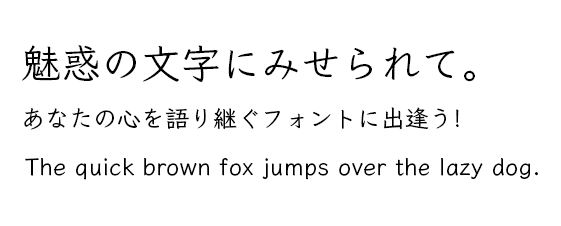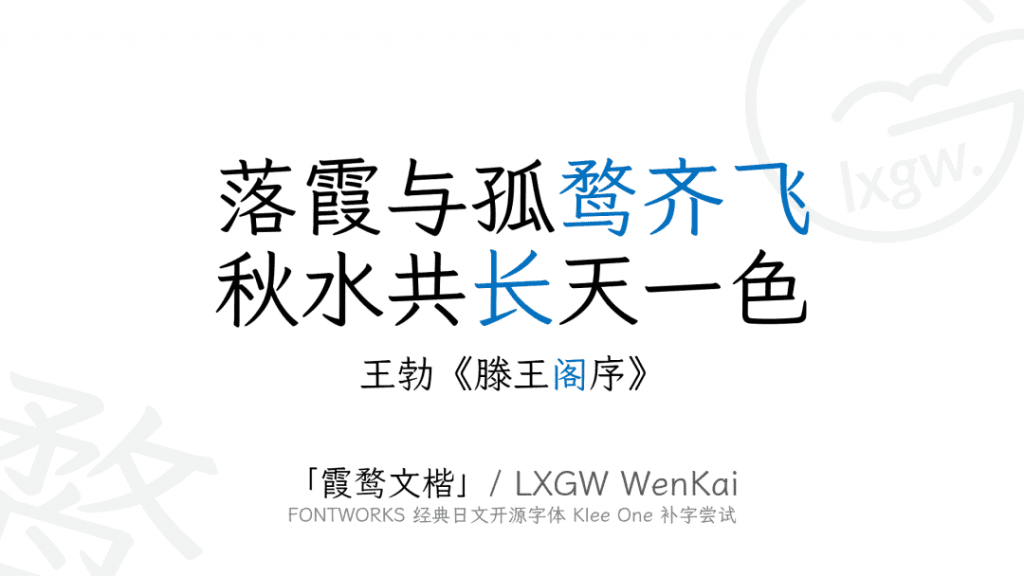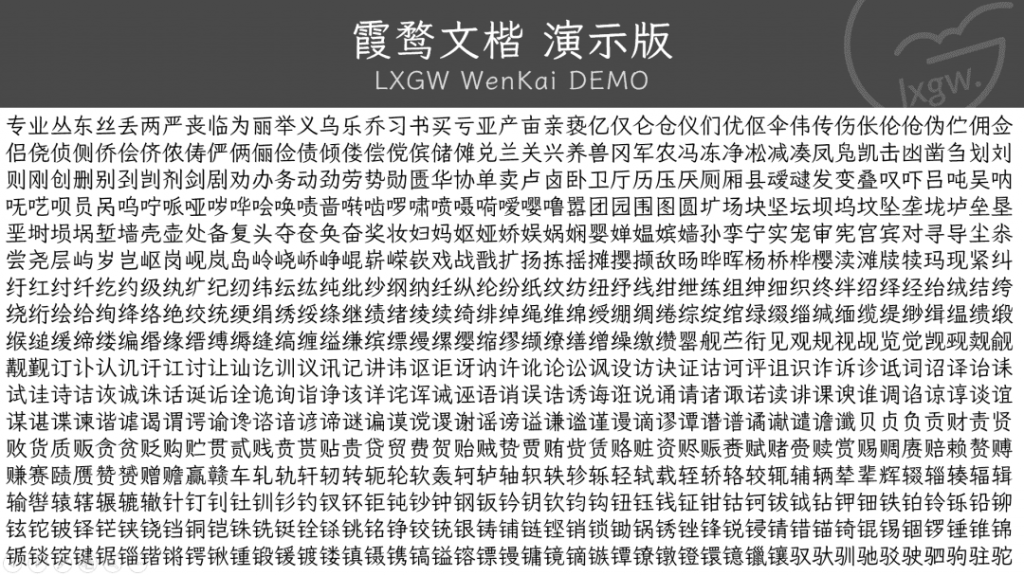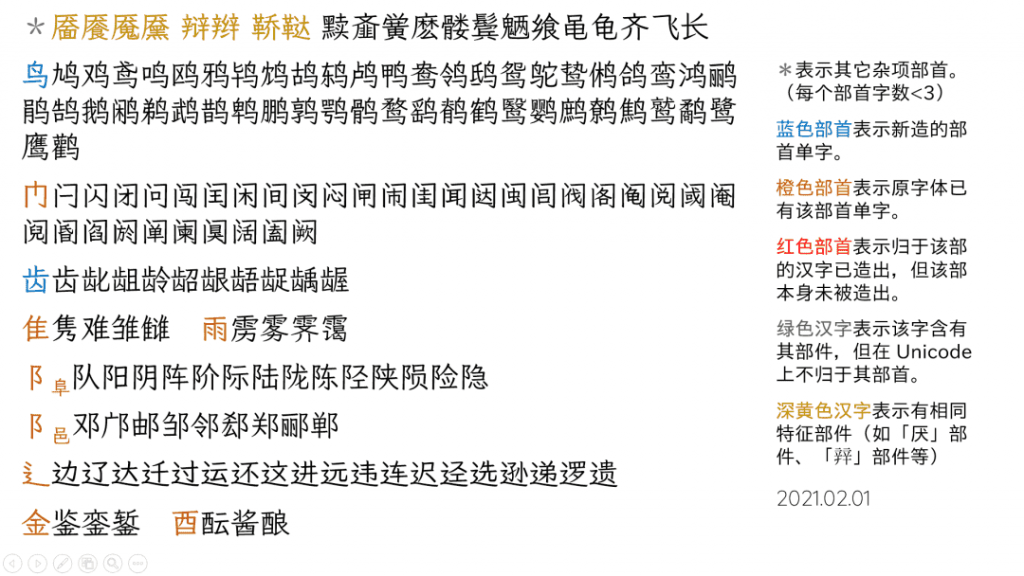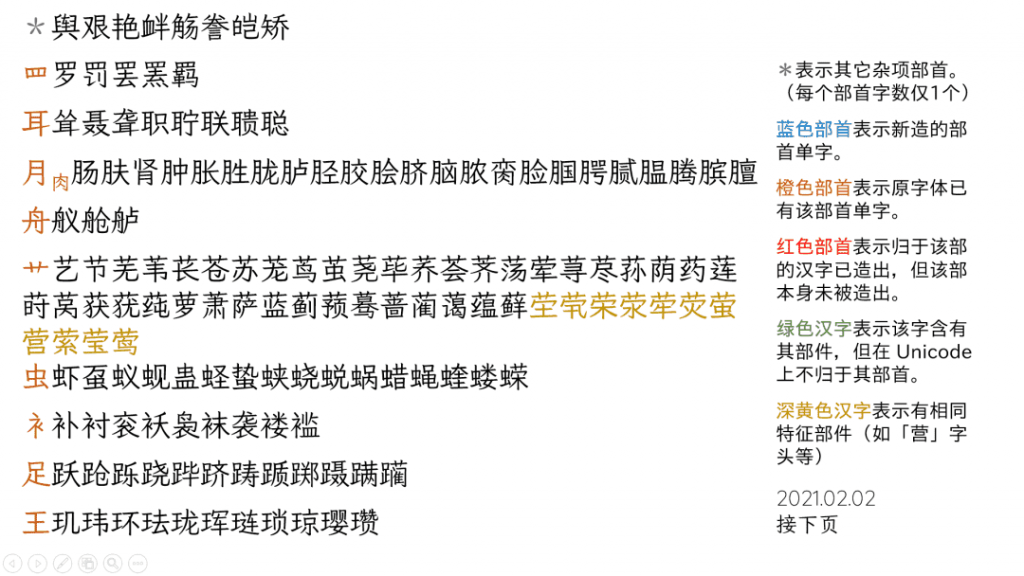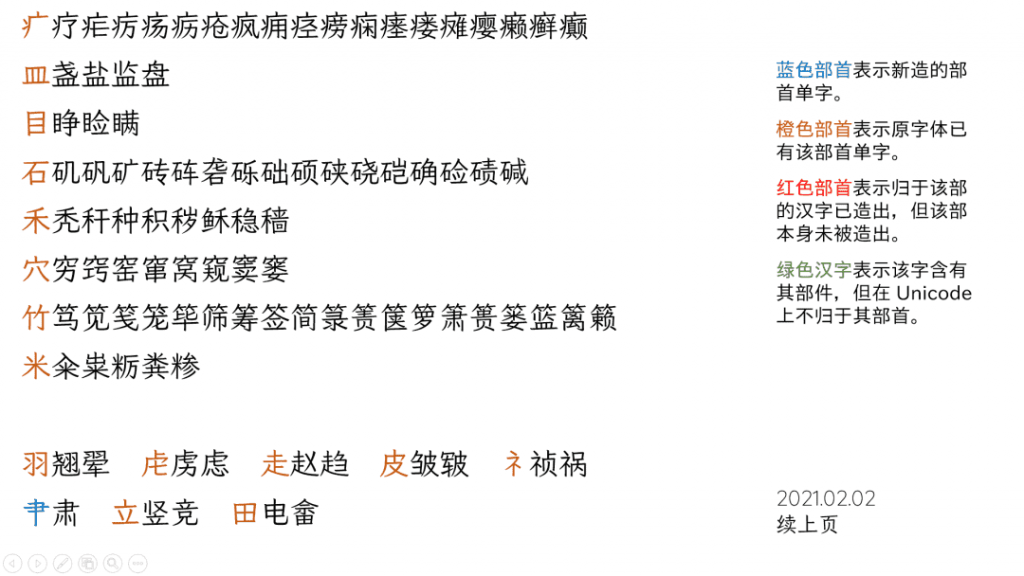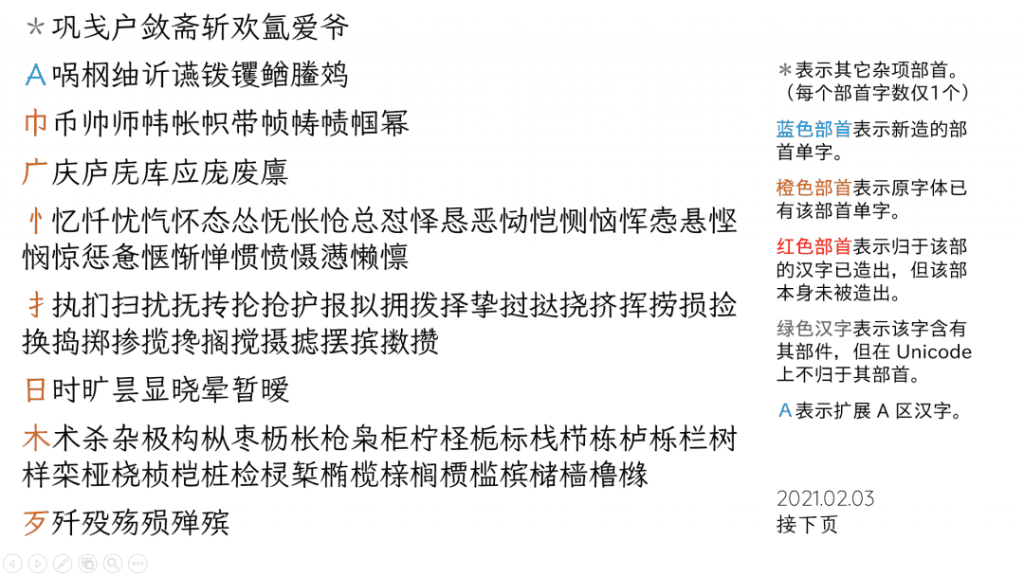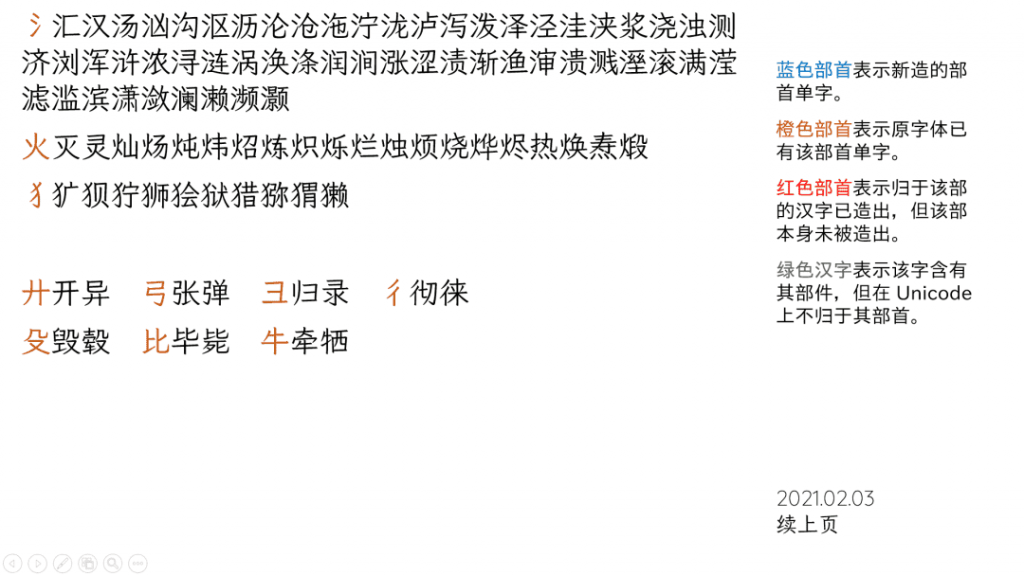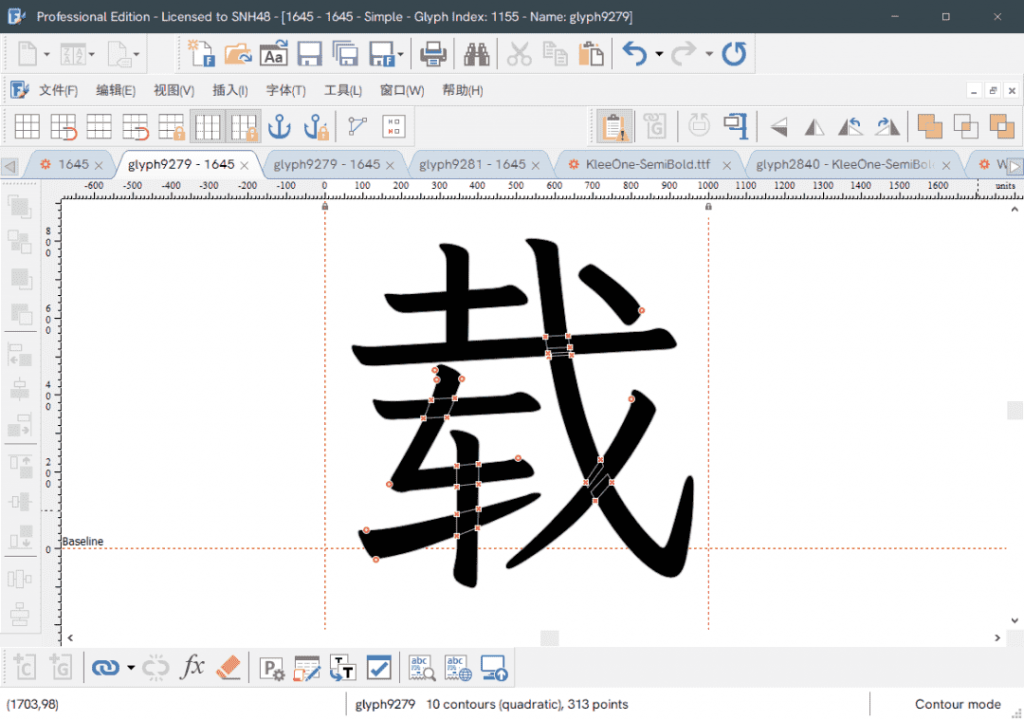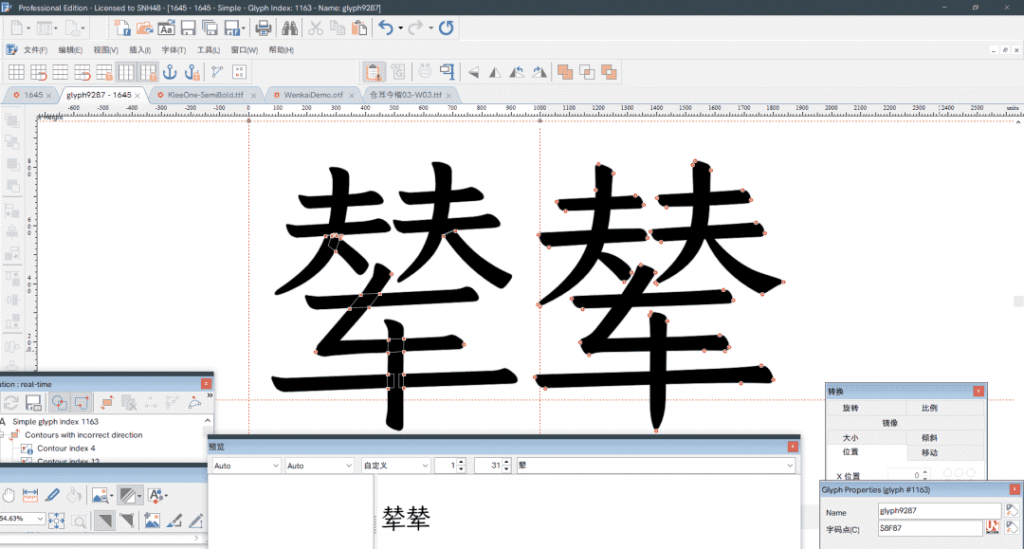
前言
前段时间,日本著名字体厂商 FONTWORKS 在 GitHub 上释出了 7 款开源日文字体,分别为 Train、Klee、Stick、Rock-n-Roll、Reggae、Rampart 和 DotGothic16。7 款开源日文字体各有各的特点,其中我最感兴趣的,当属 Klee。
FONTWORKS 公司出品过很多以西方艺术家名字为代号的字体,比如之前分享过的 Seurat、Rodin、Cezzane 等。这款字体的名字叫 Klee,是以德裔瑞士籍画家保罗•克利(Paul Klee,1879-1940)命名的。这款字体是一款日式的教科书字体(日本小学教科书的标准书写字体,相当于我们的规范楷书)。原版只有 Medium 和 Semibold 两个字重,为 Pro 字集,含有近 8000 个汉字。
初衷
这是一款本人非常喜欢的字体,有着日本教科书体的写法,兼有仿宋和楷体的特点,可读性高。一些 DIY 字体爱好者曾先后用仿宋、刻本仿宋、仓耳今楷补全这款字体,做为手机系统的美化字体移稙在 iOS、Android 等手机系统中,受到很多机友的欢迎。
不过这样补全的字体有一些不足之处。 第一,原有字体和后补字体之间有着一定的差异,致使一些不同的文字(如 Klee 原有汉字与后补简体字)混排之后会有违和感。 第二,由于补字所用的字体(如刻本仿宋、仓耳今楷等)为商业版权字体,补全之后不可用于商业用途,还会有侵权的风险。
鉴于此,本人开始了为 Klee 这一高质量的日文字体补全简体字的尝试。选取较粗的 SemiBold 字重,截至 2021.02.03,已造了1650 个字,已基本补完原字体(Klee One)所含繁体字对应的简体字。部分字稿如下图所示,持续更新。补全后的字体拟命名「霞鹜文楷」。
字稿
截至 2021.1.30 的所有新造汉字
2021.1.31 后的新造汉字
一些操作 & 后记
由于要补的字多为简体字,而原字体里没有相应部件,所以需要拆笔画。比如「车」字旁,原字体里没有简体的车字旁,就需要从别的字里用切割轮廓工具拆出「㇐」「㇜」「㇑」「㇀」这四个笔画进行拼接,缩放后还要用到加粗/减细命令。调整字形的结构,有时也需要拆笔画。用 FontCreator 拆笔画是一件烦琐且耗时的事情。
补字过程中,大多数汉字没有参照其它已有字体,全凭自己的感觉,只有少数汉字参考了仓耳今楷,也可以说是「临摹」,比如「辇」字。
下图左边的「辇」字是凭自己的感觉拼的,右边的「辇」字是参照仓耳今楷拼的。对比起来,右边的「辇」比左边的「辇」协调了很多。
由于不是专业的字体设计师,有些字基本上是直接替换偏旁,还有很多结构比例不协调的地方,还请大佬轻喷。
在这里想知道还有哪个字库公司或者设计师想要补全 Klee 这款字体,如果已经有人开始补了,我就不用费这个工夫了。
(感觉这篇文章有一点卖弄的成分)
后续
没想到有人把这些字稿转发到 Facebook 上了,居然引来了大佬们的讨论。
Francis Chow 是 Klee 系列字体的原作者,居然认为我补的简体字达到了合格水平,受宠若惊……(
此外很多人感觉补的字有点怪,我个人总结了一些原因:
- 简体字里面有很多草书楷化字,如「专车东乐练买卖贝见页」等 (对应繁体字「專車東樂練買賣貝見頁」) ,虽然这些简体字的笔画比繁体字少了很多,但比繁体字更难设计。
- 补字过程中很多字都是直接将繁体字的偏旁替换成简体字的偏旁 (如「車」→「车」、「金」→「钅」),容易造成字形结构比例失衡。
此时明白了字体设计工作是有多么的不容易,向字体设计师们致敬!
图里那几位的评论实在令人不悦,简体字又怎么了??
图里的评论是在说纟的设计跟国标不一样。
2021.02.05:目前已补完 3500 简体常用字,已上传到项目专页里的 TTF(BETA)文件夹。目前正在与北辰按照粉圆字库进一步补充繁简常用字,补完后,GB 2312 范围内的字将达到 5960。
落霞孤鶩 補的高質量開源字體 「霞鶩晰黑」「霞鶩文楷」 可以秒掉本站九成以上免費字體。
过誉了,有些补的并不好
2021-2-04 BETA版本 TTF:括号中的字体,待调整:(邀)请(函),消(毒)
等补完常用字再修改。
字体笔划非常干净、利落、有劲道。作为正文仿宋的替代字,确实很有价值!赞一个!
加油!非常期待这个字体。
原作者背书还行,厉害了